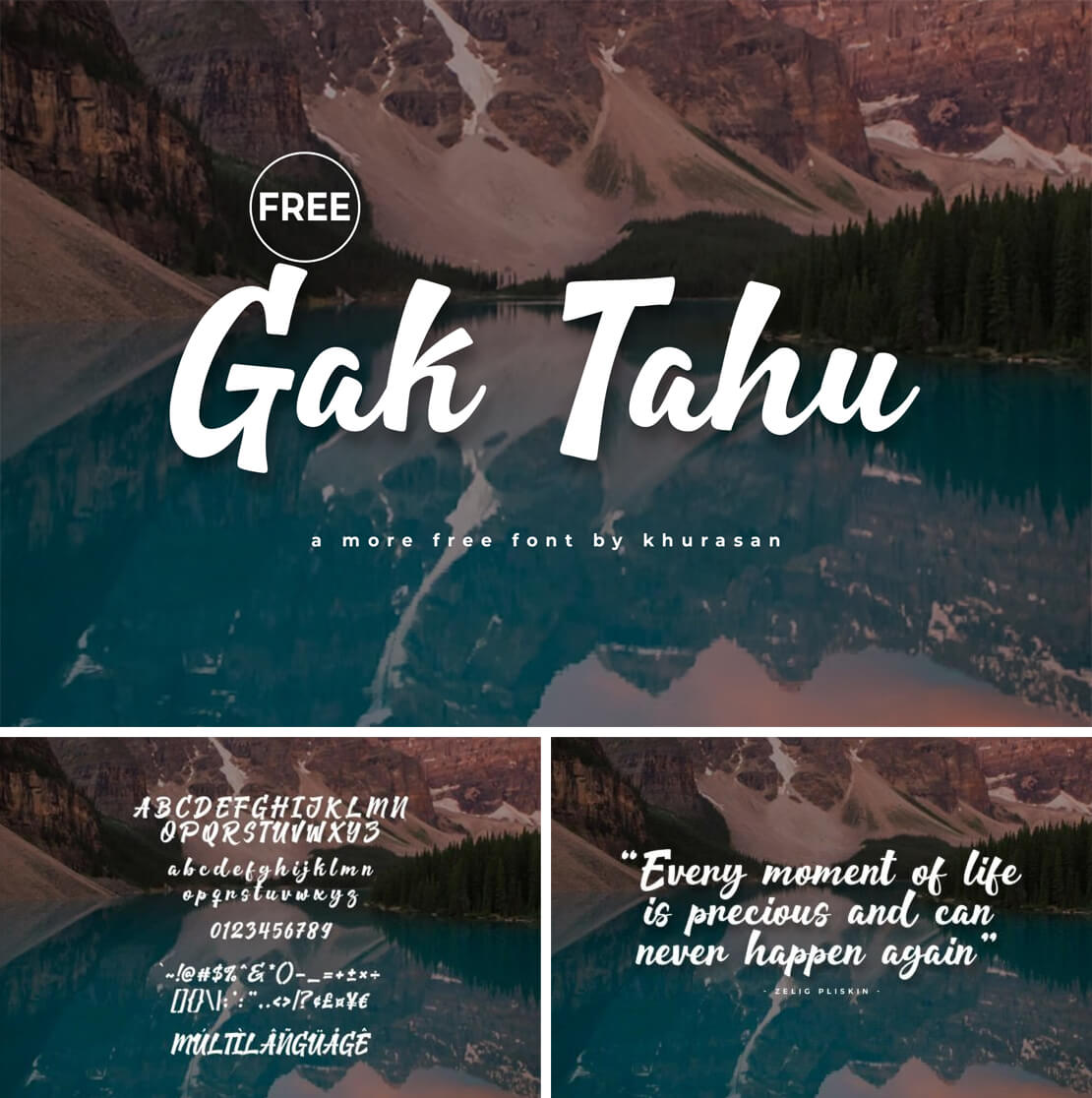
Gak Tahu
Diese Script-Schriftart wurde von Khurasan gestaltet. »Gak Tahu« bietet einen sauberen, fließenden Stil aus, der die natürliche Stiftführung nachahmt. Den Font gibt es kostenlos im Opentype- und TTF-Format zum Downloaden.
Die Monoline-Striche und die leicht geneigten Buchstabenformen verleihen der Schrift einen legeren Look. Neben einigen Sonderzeichen sind unter anderem auch deutsche Umlaute im Zeichensatz enthalten.